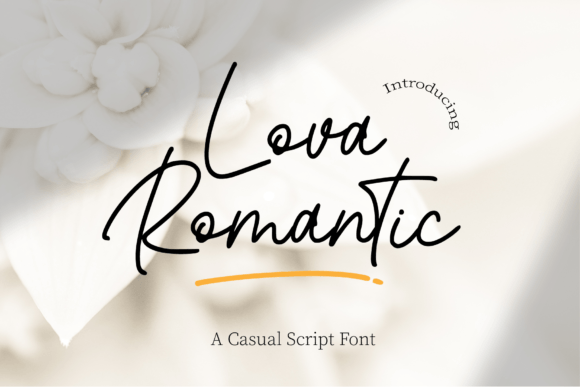
Lova Romantic
Lova Romantic gibi yüksek kaliteli varlıklar arıyorsanız, bu premium paket yaratıcı projeleriniz için harika bir seçimdir.
İster İsteğe Bağlı Baskı (POD) ürünleri, ister düğün davetiyeleri veya sosyal medya grafikleri oluşturuyor olun, Lova Romantic ideal bir uyumdur.